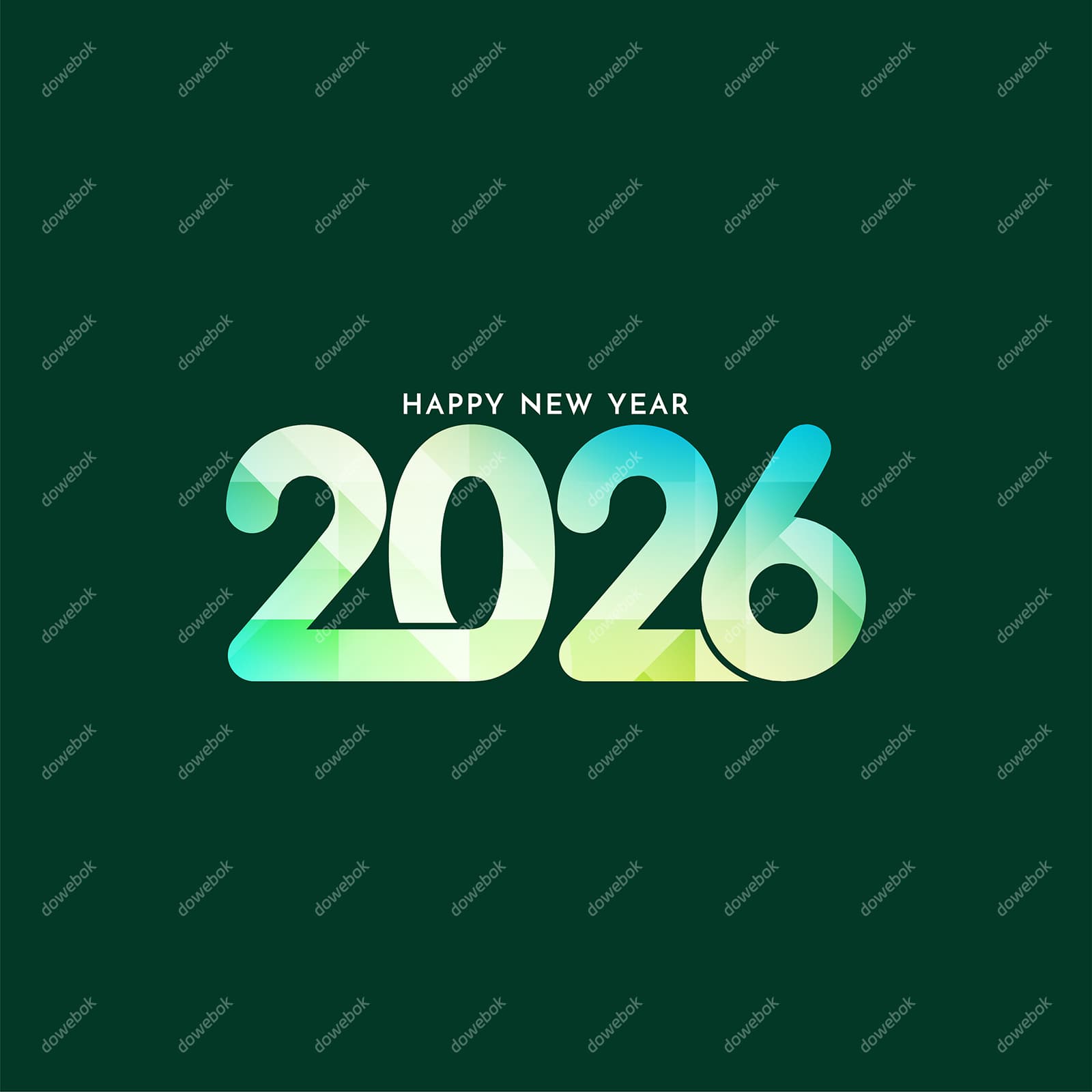
这是一款由青绿白渐变数字设计的 2026 新年快乐矢量素材,深绿背景上,“2026” 以青、绿、白渐变的几何拼接字体呈现,透明质感中透着清新灵动,上方配 “Happy New Year” 英文。整体色调柔和雅致,几何设计与渐变配色既显现代简约风格,又借清新色系传递出新年的轻盈氛围,适配简约风贺卡、电子祝福等场景,视觉舒适且富有设计感。